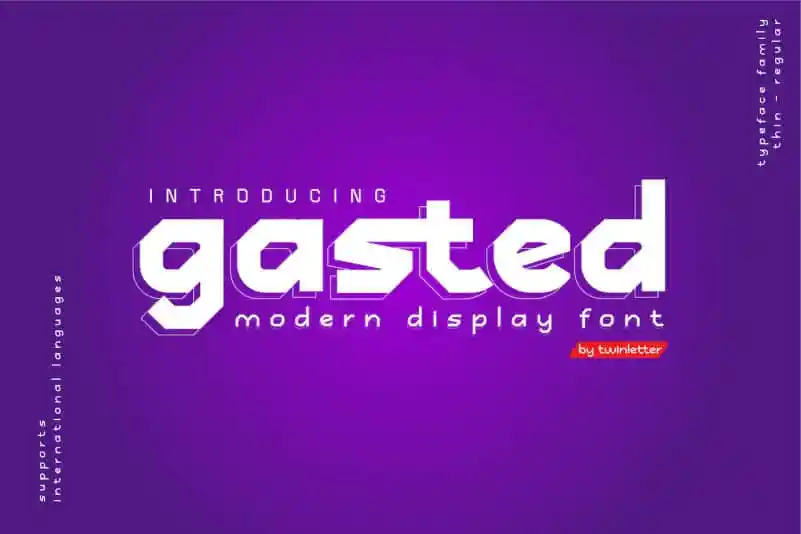
Gasted Display Font – Fonte Grátis
Gasted Display Font
Descubra a Gasted Display Font, criada por uma equipe visionária que mesclou elementos heroicos do arte escrita com modernas fontes para as necessidades digitais e robóticas. Este famoso tipo de letra san serif exalante e poderoso é perfeito para destacar seu projeto, dando-lhe um visual único e atraente. Se você está pronto para transformar seus projetos em verdadeiros obras de arte digitais, então não hesite mais e faça-o agora!